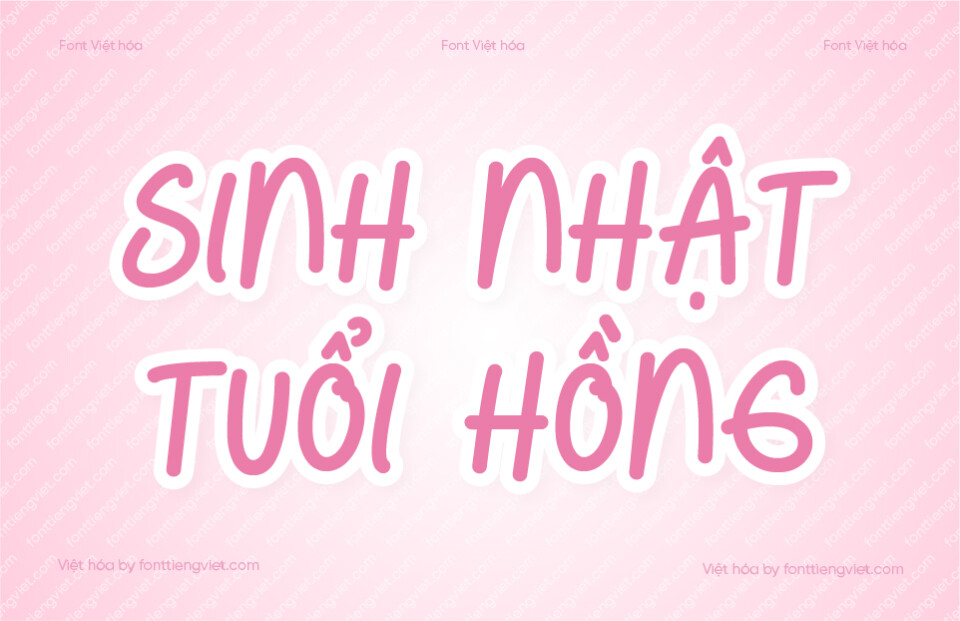
Giới thiệu về Font Việt hóa 1FTV VIP Peaceful Wishes
Trong thế giới thiết kế đồ họa hiện đại, việc lựa chọn một Font Chữ phù hợp đóng vai trò quyết định đến tính thẩm mỹ và thông điệp của sản phẩm. Font Việt hóa 1FTV VIP Peaceful Wishes là một bộ phông chữ đặc biệt, được thiết kế dành riêng cho những ai yêu thích sự nhẹ nhàng, thanh tao và mang đậm tinh thần bình an. Đúng như tên gọi của nó, bộ phông chữ này gợi lên những lời chúc tốt đẹp và sự thư thái trong tâm hồn người xem.
Đặc điểm nổi bật của phông chữ
Bộ Font Việt hóa 1FTV VIP Peaceful Wishes sở hữu những đường nét thanh mảnh, mềm mại nhưng vẫn giữ được sự chỉn chu và rõ ràng. Khác với các kiểu chữ cứng nhắc thường thấy trong soạn thảo văn bản, bộ font này mang đến một luồng gió mới cho các tác phẩm nghệ thuật. Khả năng hiển thị tiếng Việt hoàn hảo, không bị lỗi dấu là một điểm cộng lớn giúp các nhà thiết kế tại Việt Nam tự tin áp dụng vào mọi dự án từ cá nhân đến chuyên nghiệp.
Ứng dụng Font Việt hóa 1FTV VIP Peaceful Wishes trong đời sống
Với phong cách tinh tế, bộ chữ này cực kỳ phù hợp cho các mẫu thiết kế thiệp chúc mừng, bìa sách hoặc các ấn phẩm truyền thông giáo dục. Trong môi trường học đường, giáo viên và học sinh có thể sử dụng phông chữ này để trang trí slide bài giảng hoặc làm báo tường, tạo cảm giác gần gũi và dễ chịu.
Lưu ý khi sử dụng font chữ
Để đạt được hiệu quả thị giác tốt nhất, bạn nên kết hợp bộ phông này với các tông màu trung tính hoặc pastel. Việc sử dụng khoảng cách chữ hợp lý sẽ giúp nội dung trở nên thanh thoát hơn bao giờ hết.